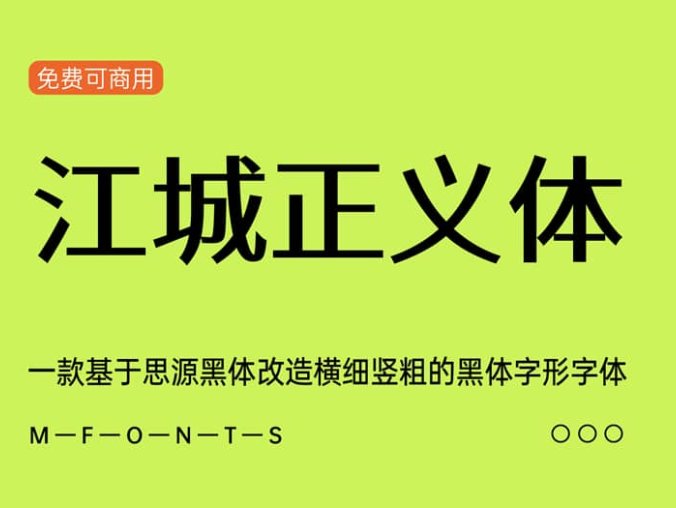
《萌神拼音体》一款以学习及普及中文为目标汉语拼音免费字体
字体简介: 萌神拼音体是用于学习中国汉字的一款字体,是使用思源宋体和M+字体进行改造而成的一款免费商用字体。 这是一种用来帮助学生更快地学习和阅读汉语的字体。在某些设计场景其实也挺实用的,特别是对教育类的设计比较有用。 基本上是可以显示日语、简体字和繁体字的字体,是在简体字和繁体字中加入拼音的字体的制作。- 0
《狮尾四季春》一款基于思源宋体的三角形改造免费可商用字体
字体简介: 狮尾四季春字体基于思源宋体的三角形改造,更加简洁现代化的字体。支持简体中文、繁体中文、韩文与日文;和思源宋体一样,支持7种字重。 相比于思源宋体,狮尾四季春的造型更加简洁明晰,版面效果清新现代轻快,缺点也比较轻,横笔明显极细。 「花园明朝」、「思源宋体」、「狮尾四季春」、「源云明体」的比较: 在「肉」、「糸」、「女」、「辶」、「食」的笔画中,狮尾比较类似台湾教育部推荐的字体笔顺,适合教…- 0
《小赖字体》一款基于濑户内海字体补全简体免费可商用字体
字体简介: 濑户字体是由日本的业余字体设计师瀬戸のぞみ制作,支持JIS第一至第四级,支持繁体和简体中文(部分)。目前最新的版本是2014年9月24日的6.20版本,原作者已经很久没有更新了。 后来,Max在原来的「濑户字体」基础上,推出了内海字体,补齐了台湾教育部门推出的4808个常用字,并增加了闽南语、粤语常用字,补充了繁体中文地区常用字缺字缺悔。 但是,这个可爱的字体,仍然缺少一部分简开源体字…- 0
《点点像素字体》一款基于文泉驿点阵宋免费可商用中文像素字体
字体简介: 点点中文像素字体是一组基于GPL 2.0协议开源发布的中文像素艺术字体,每种字体均支持超过22000个Unicode字形,覆盖GBK编码中的全部简繁体汉字。 当前的点划中文像素字体源自文泉驿项目创建的位图字体。它们是根据文泉驿位图歌曲的矢量化版本进行转换和修饰的。文泉驿点阵宋体是一款根据 GPL 2.0 授权的免费开源字体。请参阅wenq.org了解更多信息。- 0
《江城正义体》一款基于思源黑体改造横细竖粗的黑体字形字体
字体简介: 江城正义体是基于思源黑体改造,把思源黑体横向减细处理,纵向增粗处理,得到类似粗宋风格字体,这款字体削减了横笔的粗细,使字体看上去更具现代感。特别适合用于海报标题,LOGO等方面的设计。 这款字体跟日本设计师发布的源暎漫画体有点类似,但是江城正义体的横笔比源暎漫画体更细,看上去更有特色。另外,源暎漫画体是使用日本版的思源黑体改造的,所以对简体中文支持并不好,并且只有一个字重。而这款江城正…- 0
《江城圆体》一款比较适合国内设计师使用的圆体字形
字体简介: 一位被设计耽误的程序大神刘鹏,基于源泉圆体进行改造,把一些台湾习惯的字形进行简体化修正,发布了一款比较适合我们大陆设计师使用的字体”江城圆体“。 这款字体基本源泉圆体改造,所以简体也是不缺少字的。并且有6个字重,十分贴心。- 0
《狮尾肉丸体》一款游走于古典与可爱之间的免费商用中文字体
字体简介: 狮尾肉丸体(Swei Meatball)是台湾的字体设计师 MAX 基于思源宋体进行修改,创造的一款新字体。 将思源宋体字形中的三角形替换半圆形改造而成,从而使得字体更加简明现代化。本款字体支持简体中文、繁体中文、韩文与日文,和思源宋体一样,狮尾肉丸体同样拥有 7 个字重,能满足大部分的设计需求。 在字体细节方面,日本字体做的比较细致,常见的缺点比较容易缺字,笔画方面也有点不太一样。由…- 0
《悠哉字体》基于日系手写字体 Y.OzFont修改制作
字体简介: 悠哉字体是一款基于Y.OzFont的手写风格的字体。利用原字体中已有的笔划和部件,通过拼接和调整造出新字 (必要时自己用鼠标写出部件) 。目前已补全原字体中有对应繁体字的简体字,以及GB 2312范围内的所有汉字,并根据jf Open 粉圆的字库补全了繁体中文的常用汉字 (包含台湾教育部门规定的 4808 个常用汉字) 。 悠哉字体在原Y.OzFont的基础上,字面缩小至原来的95%,…- 0
《一点明体》一款展现传承汉字构字的科学系统 原刻石录明体字体
字体简介: 2020.9.17更新记录:一点明体已于近期更新7.00版本,除了原来的正体(繁体)、日韩汉字、粤台闽客汉字等传承字形,以及注音符号、麻雀版、苏州码子,象棋等,也制作了旧字形的简化字,不会再碰到繁简不分的问题。无论正简日韩,都可以选择美观、平衡的传承字形!该字体对应的下载链接我们也已经更新至最新版! 一点明体(一點明體、I.Ming)的前身是刻石录明体,已由开源字型组织I.字坊(日本 …- 0
《站酷仓耳渔阳体》一款方圆结合厚重又不失灵动的免费可商用字体
字体简介: 站酷仓耳渔阳体是仓耳字库在2020新冠疫情期间为造福社会奉上的一份礼物,也是站酷冠名的首款拥有家族字体的公益字库。字形结合宋、黑二体的结构特点,将部分笔画转折处做圆角处理,方圆结合,厚重又不失灵动。家族字体包含5个字重,均可免费商用,2020年9月发布第一版。 字数:本字体基于中华人民共和国GB2312-80字符集汉字部分标准,有TrueType和OpenType两种格式,共收容汉字6…- 0
《千图小兔体》一款随意放松充满卡通趣味的手写免费可商用字体
字体简介: 千图小兔体是千图网联合国内专业字体设计机构iFonts共同发布的一款萌系创意字体,历时半年多悉心打磨完成。向所有千图网用户开放免费下载。将可爱的千小兔融入字体设计中,尽显年轻、活力与俏皮,适用于可爱、少女风的海报、店招等场景。 字体样式:- 0
《摄图摩登小方体》一款摄图免费商用公益字体暖心上线“益”起爱的字体
字体简介: 摄图摩登小方体是摄图网联合国内专业字体设计机构iFonts共同推出的一款公益创意黑体字。 采用GB2312编码,共包含6995个字符,其中6763个简体汉字,52个大小写字母,10个数字,170个标点符号。 作为公益开源字体,摄图摩登小方体已经向全社会开放下载并可免费商用啦(包括个人及企业商业用途)。 字体的设计灵感来自对未来空间的想象,传达给人一种未来与现实的交际感。 笔画方正质朴而…- 0
《仓耳非白 》一款粗细对比明显风格强烈免费可商用字体
字体简介: 仓耳非白是一款粗细对比明显、风格强烈、拥有5个字重的家族字体,结构方整,笔形简洁、利落,带有明显区别于其他字体的风格。设计时,除了加粗笔形强调“黑”,也增加了部分细线强调“白”,字形转折处均做直角处理,撇捺同样以直线表现,最终成字呈现强烈的粗细对比。点的部分改为圆形,方圆结合,整体结构更加柔和。 本字体基于中华人民共和国GB2312-80字符集汉字部分标准,TrueType格式,共收容…- 0
《仓耳与墨》一款刀走凌云 将篆刻的“刀意”融入其中现代创意字体
字体简介: 仓耳与墨是一款包含5个字重的家族字体,风格偏向现代创意字体,强调厚重与力量,具有醒目、有力和前卫的特点。 字体将篆刻的“刀意”融入其中,在笔形处理时模拟了类似篆刻的刀刻痕迹,同时为中和这种“尖锐”,在转折和“口”字结构上使用圆转角的处理方法,让整个字内方外圆。配套使用的英文和标点部分也同步沿用了与中文相同的设计特点,在混排时风格统一,不会突兀。 本字体基于中华人民共和国GB2312-8…- 0
《仓耳舒圆体》一款笔形一端较粗一端较细 自然过渡圆润饱满的字体
字体简介: 苏轼有词云“缺月向人舒窈窕”,尚未圆满的月亮像安静的美人,动作舒缓。仓耳舒圆体的笔形一端较粗一端较细,自然过渡,圆润饱满,端庄中带有几分慵懒,轻松愉悦,字形轮廓整体统一。家族字体包含5个字重,均可免费商用,2020年9月发布第一版。 本字体基于中华人民共和国GB2312-80字符集汉字部分标准,TrueType格式,共收容汉字6763个,英文及标点等常用字符245个。 字体样式:- 0
《仓耳小丸子》一款天真浪漫调皮可爱搞怪的买南非可商用中英文字体
字体简介: 仓耳小丸子结构灵活,选用粗细对比夸张的笔画,使字体更具视觉冲击力,搞怪的字型结构和出乎意料的空间调整让字体多了几分调皮可爱之气,笔画错落有致,打破了许多固有的排列模式,这款字在宽松的氛围中营造出天真烂漫的感受。 本字体基于中华人民共和国GB2312-80字符集汉字部分标准,TrueType格式,共收容汉字6763个,英文及标点等常用字符245个。 字体样式:- 0
《字体传奇南安体》字体传奇第二款免费字体
字体简介: 字体传奇南安体-是字体传奇网(福建)字友-吴金彬设计-字体传奇编码完成的一套免费商用字体,字体的起名是吴金彬以他的家乡南安命名的,他把这款字体,贡献给大家永久免费商用,也希望大家记住吴金彬和他的家乡南安。 设计用时:1年多 简体中文:6763 支持:Win/Mac 风格:艺术字家族 字库编码:张家佳字体团队 吴金彬言:我一直在寻找一个可以干到老的工种,毕竟人总是会老的种田我又不会,兜兜…- 0
《优设标题圆》优设出品的第4套免费商用字体
字体简介: 优设标题圆!1 月 10 日正式上线!在保留「优设标题黑」的力量感的基础上,去除倾斜、增加圆角,整体更加温和圆润,同样是免费可商用。 同步上线的还有优设的第一套手写书法体:优设书华体。结合传统书法与当下潮流手写字体,无论是国潮风、美食还是商品促销页都堪称百搭,想做2022年相关页面的设计师,这款尤其适合。 字体样式:- 0
《龚帆免费体》一种视觉坊高质量毛笔字体 开放全网下载免费字体
字体简介: 龚帆免费体是视觉坊发布的一款高质量的免费商用毛笔字体,这款字体含3000+常用的简体中文字形,能满足一般的设计需求。 字体样式:- 0
《标小智无界黑》一种脱胎于日本开源德拉黑体的超粗黑体免费字体
字体简介: 标小智无界黑,是由标小智LOGO神器携手猫啃网一起创作设计的第一款品牌字体,允许任何个人和企业免费使用,包括商用用途,无界无限制字如其名,愿为中文免费字体生态添砖加瓦,来一起看看这款非常酷的免费商用中文字体吧! 标小智无界黑是一款脱胎于日本开源字体——德拉黑体的超粗黑体,标小智无界黑按照GB2312-80字体标准来制作,从字库角度出发,将原字体中的汉字字形更改为更加符合国标的字形,在字…- 0
《演示夏行楷》一款夜热依然午热同 开门小立月明免费可商用字体